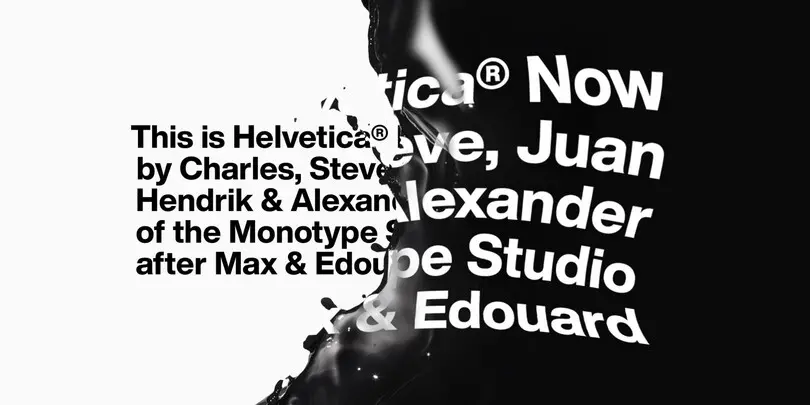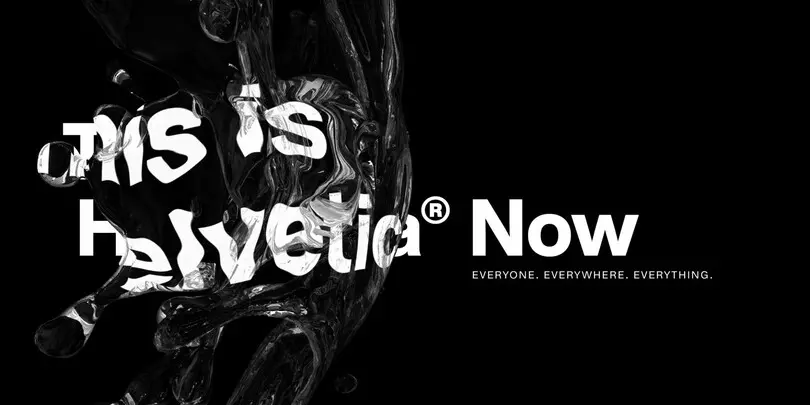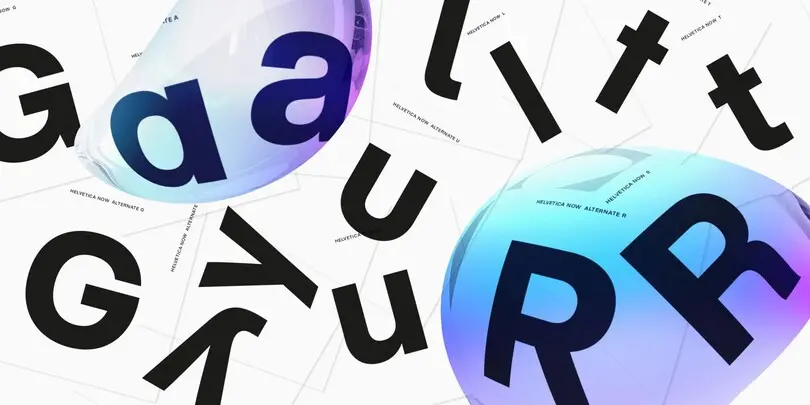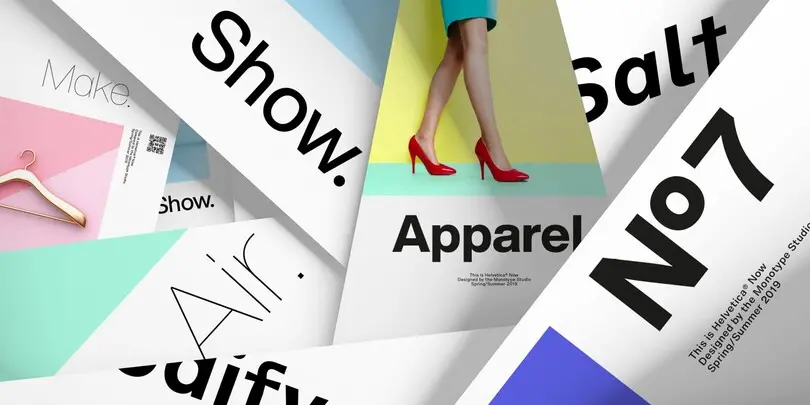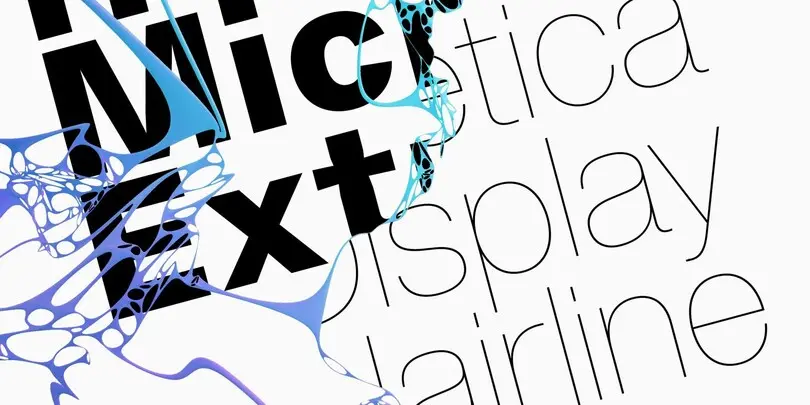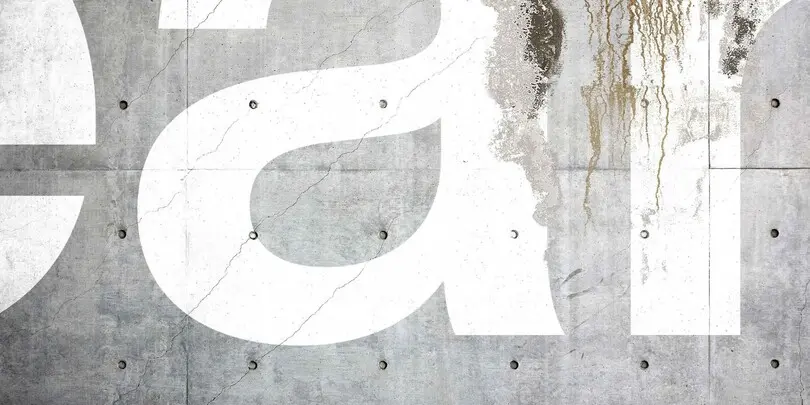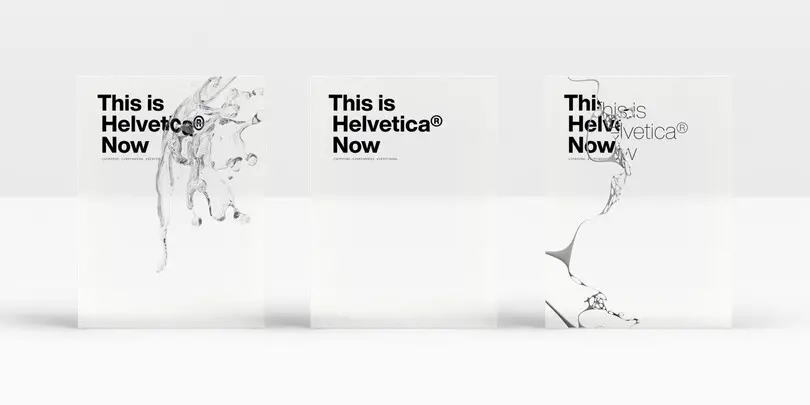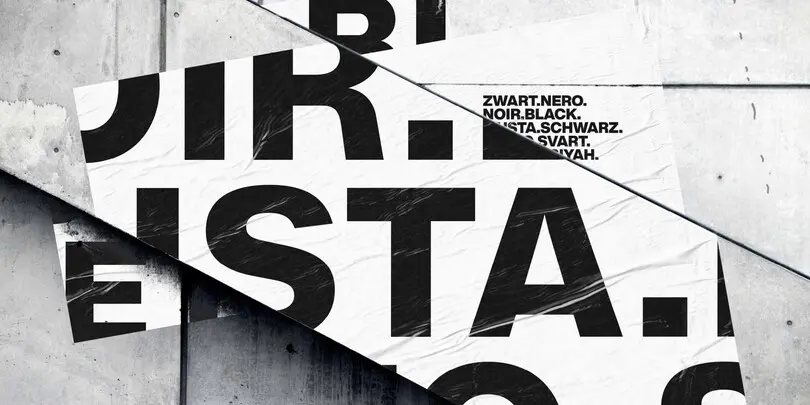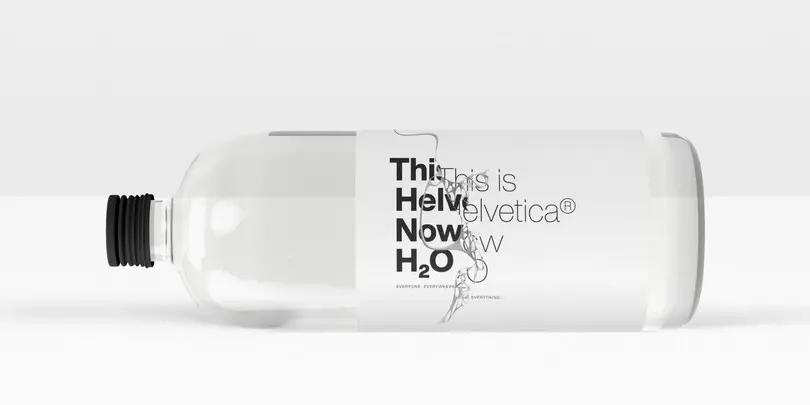
Neue Haas Unica
La famille New Haas Unica™ est une version élargie et remaniée de l’Haas Unica®, une alternative à l’Helvetica® qui a atteint un statut quasi-culte dans la communauté des fontes de caractères avant de quasiment disparaître. Publiée par la fonderie de type Haas en 1980, aucune mise à jour n’a rencontré le succès dans les environnements numériques actuels. Jusqu’à présent.
Neue Helvetica®
La fonte créée par Max Miedinger et ses collaborateurs dans la fonderie typographique Haas est devenue une des fontes les plus connues et les plus appréciées au monde grâce à la stratégie de marketing de Stempel et de Linotype. Elle fait partie intégrante de beaucoup d’imprimantes de bureau et de systèmes d’exploitation. La conception der lettres d’origine de Helvetica a dû être adaptée au système Linotype. Au fil des ans, la famille s’est agrandie de plusieurs fontes qui n’harmonisent pas parfaitement entre elles.
C’est pourquoi la société D. Stempel AG réorganisa et numérisa la famille en 1983 pour Linotype et en lança avec Neue Helvetica une version harmonieuse sur le marché. Aujourd’hui, cette famille se compose de 51 découpes.
Sabon
Au début des années 1960, la fédération des imprimeurs allemands demanda qu’une nouvelle fonte soit créée pour être utilisée de manière identique sur les machines de type Linotype et Monotype pour que les textes et les fontes soient en conformité. Walter Cunz, de la société Stempel AG, demanda à Jan Tschichold de créer une nouvelle version du Garamonds Roman classique. L’aspect de la découpe épaisse et surtout des cursives étaient limités par les conditions techniques des machines de coulée du type Linotype, de telle manière que la largeur de caractère des lettres était la même pour toutes les fontes, ce qui conduisit à la forme étroite caractéristique du f en italique.
On doit le nom de la fonte à Jacques Sabon qui jadis apporta la Garamond Roman à Francfort. Sabon est la fonte préférée de beaucoup de typographes quand il s’agit de fixer des lettres, d’une part parce qu’elle est agréable à lire mais surtout parce que les recommandations de Jan Tschichold concernant la typographie des livres sont encore d’actualité.
Sackers Gothic™
Sackers Gothic appartient au groupe des Sackers, une série de fontes qui furent créées d’après un modèle de Sackers, un héliograveur de Charlotte, en Caroline du Sud, célèbre pour sa fabrication de lettrage gravé destiné aux cartes de visite . Depuis cette époque, Sackers Gothic est une fonte appréciée pour donner une note élégante et franche à la conception d’enveloppes de protection, de posters et de papiers à lettre. Son apparence se lie bien avec les lettres contrastantes des titres ou bien alors, on s’en sert pour tout ce qui est appelé à rayonner une certaine finesse typographique.
Slate™
Avec 8 graisses et 2 largeurs, la collection Slate s’avère être très polyvalente : une excellente lisibilité, tant en impression qu’à l’écran. Slate a été conçue par le typographe primé Rod McDonald, qui a réussi à combiner les meilleures caractéristiques des formes de lettres humanistes et grotesques : « Je voulais un design pur… et j’admets que j’ai été impitoyable avec toutes les lettres qui voulaient se démarquer du groupe. »
VAG Rounded™
La famille VAG Rounded™, qui a été commandée en 1979 comme nouvelle font d’entreprise pour Volkswagen AG, se caractérise par des extrémités de lignes clairement arrondies, ce qui donne à la font un aspect convivial et attrayant. La famille, développée par Wolf Rogosky et Gerd Hiepler, a été introduite pour toutes les filiales du groupe et a assuré l’uniformité de l’image de marque du groupe. La conception a été publiée pour une utilisation extérieure en 1989 et fut associée à de nombreuses solutions de publication assistée par ordinateur disponibles à l’époque. Cela a permis à des millions d’utilisateurs d’ordinateurs d’utiliser cette font de caractères la plus populaire au monde.
Futura Now
Futura® Now, l’ultime version de la famille ayant donné à la typographie moderne sa définition, contient 102 styles (incluant des sous-familles Text généreuses en espace et Headline plus condensées). Son alignement contemporain des noms et des graisses apporte une expérience utilisateur améliorée. Elle est aussi disponible sous forme de police variable — déployant des styles illimités dans une empreinte digitale ordonnée.
Neue Kabel®
Marc Schütz, qui enseigne la conception de caractères à l’Offenbach Academy of Design, a relevé le défi d’actualiser et de repenser la conception originale de la police Kabel®. Son but était de créer des formes qui seraient performantes dans les environnements visuels modernes tout en conservant le caractère et le charme originaux de Kabel.
Neue Kabel conserve l’esprit du design de Koch et le complètent avec les caractéristiques cohérentes et la structure familiale d’une police du 21e siècle. Les corps de texte en Neue Kabel résonnent avec l’élégance et le caractère ludique du design de Koch, offrant une polyvalence qui permet à cette police d’exceller dans un large éventail d’environnements imprimés et interactifs.
Wolpe Pegasus
Wolpe Pegasus fait partie de la collection de polices de caractères Wolpe et célèbre toutes les incohérences et les empattements surdimensionnés et non assortis du dessin original de Pegasus dans un jeu de caractères élargi. La collection Wolpe célèbre l’œuvre exceptionnelle de Berthold Wolpe et comprend cinq polices de caractères emblématiques, numérisées et mises à jour par Toshi Omagari du Studio Monotype.
H&M
Les supports écrits de la société suédoise de vêtements H&M sont par exemple des publicités, des catalogues, des emballages, des vidéos et des affiches. H&M ayant déjà travaillé avec une police sans serif exclusive appelé HM Ampersand (également conçue par Monotype) la société souhaitait développer un langage typographique plus complet et moderne qui pourrait fonctionner sur tous les canaux et dans tous les pays.